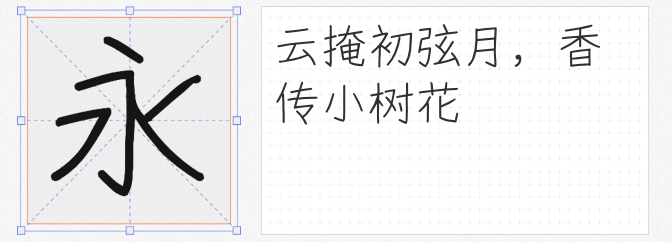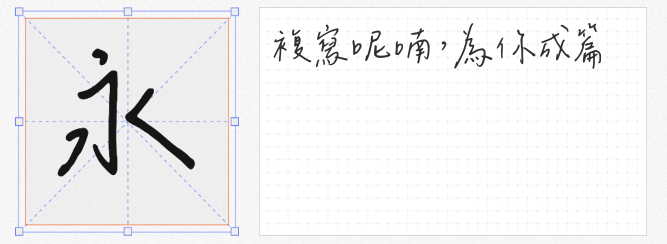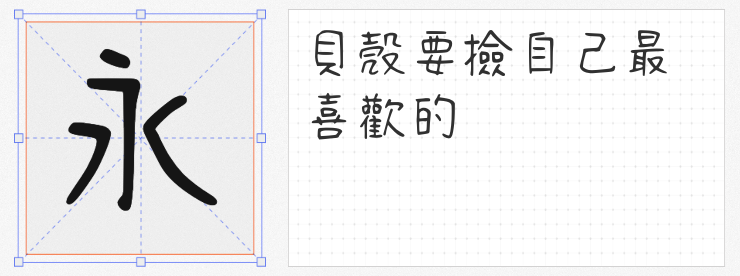
在追求个性化与情感化的设计趋势中,手写字体的独特魅力愈发凸显。其自然的笔触、灵动的形态,能为作品注入鲜活的人文气息。以下四款免费商用且适配多场景的手写字体,兼顾实用性与艺术性,助力设计师轻松打造有温度的视觉表达。
1. 悠哉字体 细体
基于经典手写风格字体Y.OzFont优化升级,悠哉字体 细体通过精细化补全与调整,实现了简体、繁体及通用规范汉字的全覆盖(超8105字),满足多元设计需求。字面缩小至原版的95%,搭配优化后的西文与标点符号,整体更显精致紧凑。其笔画在保留手写韵味的同时,贴近内地规范字形,适用于书籍排版、品牌包装等需要兼顾规范性与艺术感的场景。
2. 写意体SC
以中性笔书写质感为灵感,写意体SC通过补全简体字库并调整字形结构,打造出简洁流畅的视觉风格。字体笔画粗细均匀,转折处利落干净,既保留手写的自然感,又具备现代设计的简约气质。适用于海报标题、社交媒体图文等需要突出个性与易读性的场景,为文字赋予轻盈的呼吸感。
3. 清松手写体2
由设计师游清松以原子笔在稿纸上手写生成,清松手写体2真实还原了日常书写的自然状态。笔画中略带抖动的痕迹与不规则的粗细变化,传递出未经修饰的生活气息。这款字体特别适合餐饮品牌、手账素材或儿童读物设计,以质朴的笔触拉近与受众的距离。
4. 辰宇落雁体 Thin
作为学生自主学习计划的成果,辰宇落雁体Thin以纤细的笔画与舒展的结构,营造出空灵优雅的视觉氛围。其手写形态如信笺上的私语,既适合文艺类品牌Logo、婚礼邀请函等浪漫场景,也能为科技产品宣传增添人文温度。字体的每一处笔触都仿佛在诉说故事,让设计更具情感深度。
四款字体各具风格,或规范、或极简、或生活化、或隽永,均支持免费商用。选择契合设计主题的手写字体,即是赋予文字以生命,让视觉表达更具感染力。